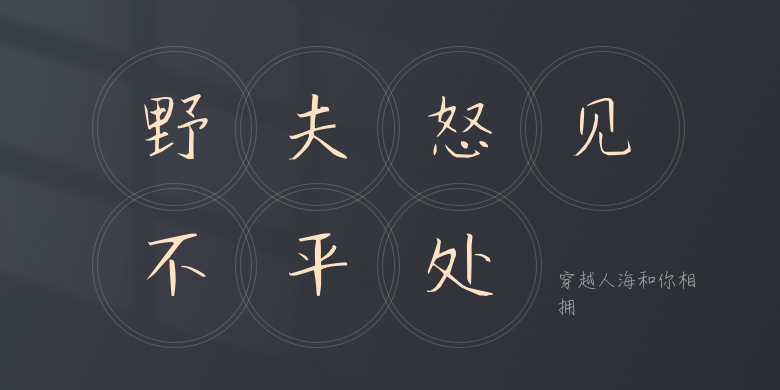
穿越人海和你相拥
穿越人海和你相拥,这款字体结构工整、笔画清晰,兼顾美观与易读性,适用于标题、正文、海报、包装、LOGO 等多种场景。字形优雅稳定,风格百搭耐看,适配日常排版与创意设计,让文字呈现更舒适、更具质感。穿越人海和你相拥一笔一画,皆是细节,以均衡的比例、流畅的线条打造舒适视觉体验,字形端正大气,风格简约现代。无论是商业设计、品牌宣传还是日常排版,都能轻松驾驭,让文字更有格调与力量。穿越人海和你相拥字体下载。